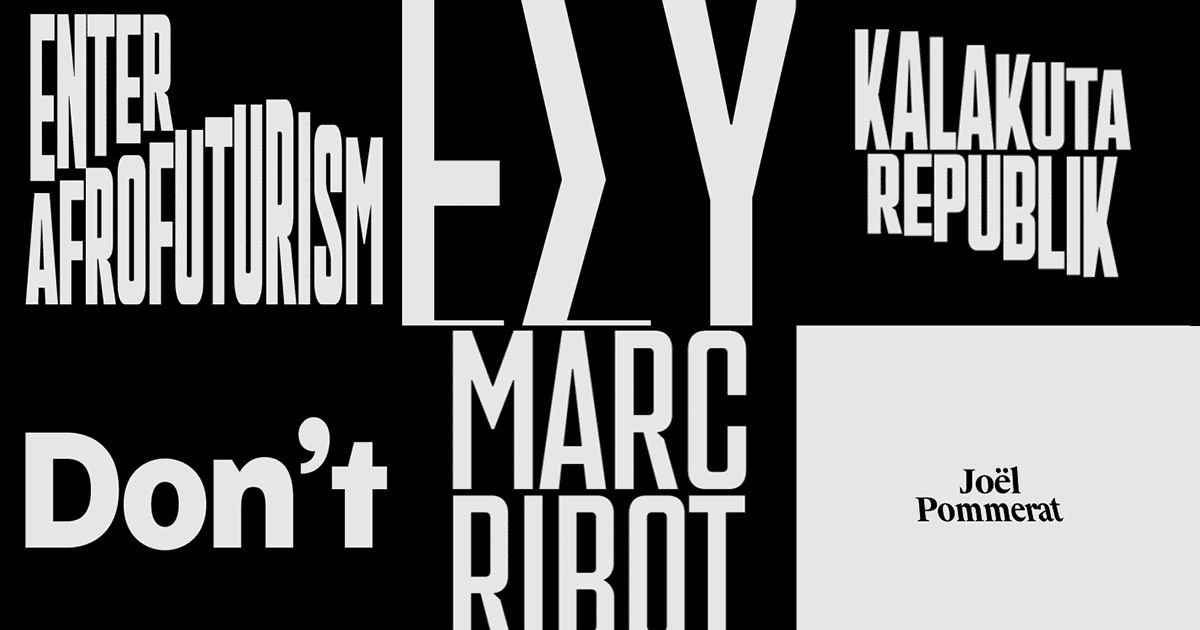
Da nueva vida a tus tipografías con Flow Type
Una herramienta tipográfica gratuita para retorcer tus textos de la forma más orgánica posible
Cuando el Onassis Cultural Centre, una de las instituciones culturales más importantes de Grecia, encargó a la agencia Beetroot Design una reformulación de su identidad visual, éstos apostaron por un acercamiento decididamente tipográfico: letras expresivas, juguetonas y orgánicas para llegar al público más amplio posible.
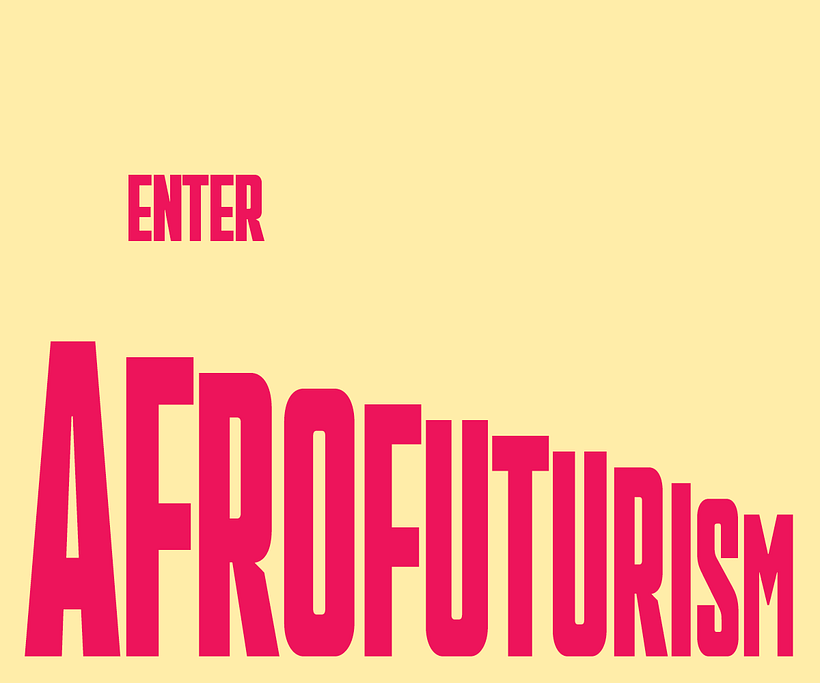
Con el objetivo de que sus caracteres se comportasen de la forma más natural posible, apareciesen en la hoja como si realmente hubiesen crecido antes, Beetroot desarrolló Flow Type: un software tipográfico que permite que tiempo y movimiento se expresen de forma orgánica en aquellas tipografías en las que se aplica, convirtiendo los caracteres en figuras con vida propia que crecen, se encogen, se acercan y se alejan gradualmente. Un recurso extraordinario que les permitió llenar de vida y dinamismo la temporada 2017-2018 del OCC, y que ahora ofrecen también a todo aquel que busque composiciones tipográficas inesperadas y sorprendentes.